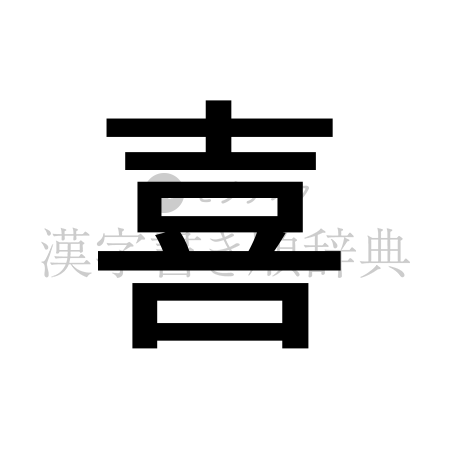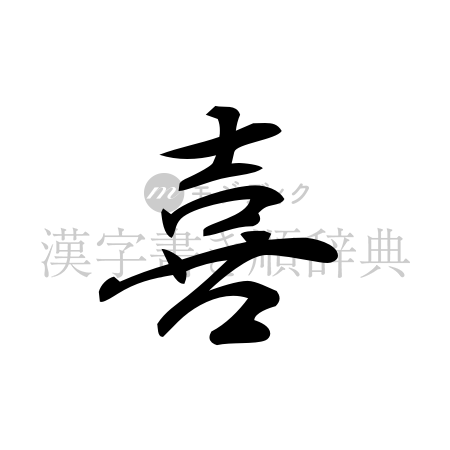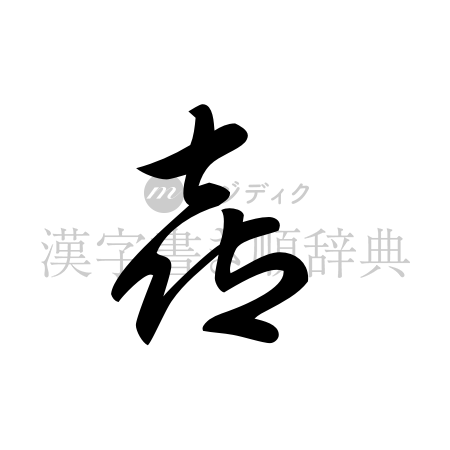
漢字「喜」(キ)の書き順・読み方・意味・部首・画数
「喜」の書き順動画アニメーション(12画)
「喜」の書体
• 喜の書体「ゴシック体」のイメージ
• 喜の書体「明朝体」のイメージ
• 喜の書体「教科書体」のイメージ
• 喜の書体「楷書体」のイメージ
• 喜の書体「行書体」のイメージ
• 喜の書体「草書体」のイメージ
• 喜の書体「隷書体」のイメージ
• 喜の書体「篆書体」のイメージ
「喜」の意味
• 喜ぶこと、嬉しいこと。
• 楽しむこと。
• 祝い事、めでたいこと。
• 笑顔や笑い声。
• 喜びを表現すること。
• 感謝の気持ち。
「喜」の意味の英訳
漢字は1文字で多様な意味を持ちますが、「喜」を英語で表す場合、一般的には rejoice, take pleasure in などがあります。
「喜」の成り立ち・由来
六書分類 会意文字
構造 壴(太鼓)+口(くち・笑い声)
「喜」は、上部の「壴」と下部の「口」を組み合わせた会意文字です。「壴」は台の上に据えた太鼓をかたどった形で、めでたい席で打ち鳴らす楽器を表します。下の「口」は、笑う口や喜びの声を示しています。太鼓の音に合わせて声をあげて笑い楽しむさまから、「よろこぶ」「うれしい」「めでたい」という意味を表すようになりました。現在の字形では上部が「吉」に近い形となっていますが、もとは太鼓を描いた「壴」に由来します。
喜悦 - きえつ
心から喜ぶこと。心からの強い喜び。
喜劇 - きげき
諧謔(かいぎやく)・機知・風刺などに富む演劇。
歓喜 - かんき
非常に喜ぶこと。また、大きな喜び。
「喜」は名前に使える漢字です。